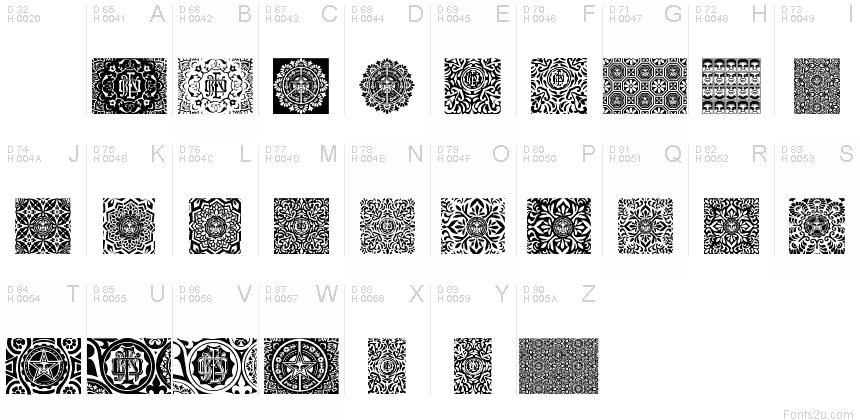
Obey Patterns, entworfen von Bob is the Owl für Metaphase Brothel Graphix, ist eine kostenlose ornamentale Dingbat-Schrift aus dichten, symmetrischen Motiven. Blumenranken und spitz zulaufende Blätter strahlen um ein strenges zentrales Gesicht herum und verleihen jedem Zeichen das Aussehen eines geschnitzten Emblems.
Sie kann ein Poster oder ein Albumcover eher in ein sich wiederholendes grafisches Feld als in gewöhnliche Schriftzüge verwandeln. Diese Mischung aus Porträtmedaillon und Blattwerk eignet sich zudem für Streetwear-Merchandise und Event-Grafiken und verbindet die Anwendungsbereiche durch eine markante Siebdruck-Ästhetik.